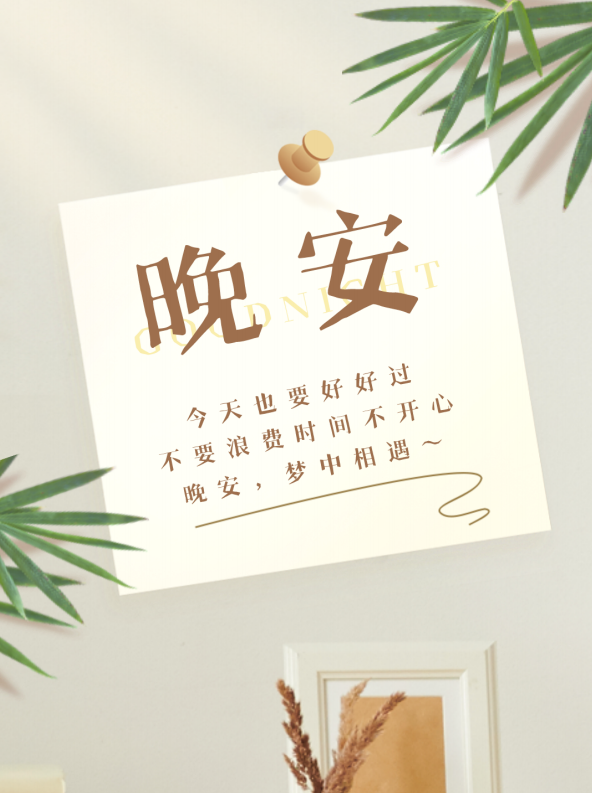
高手庆科手绘宋
Master-ZqkshouhuisongGB
该字体是一款手写感为基础的宋体,字体设计生动灵活。笔画设计保持传统宋横细竖粗的特点,曲线硬朗。横笔画末端加入三角形装饰角,长撇笔画加入转折,与传统宋体撇笔画形成强烈对比,钩笔画笔形细长,略微上挑,具备更强的趣味性的视觉效果。
沿袭中文的设计特点,西文符号以直硬转折的直线为主,加西文风格和中文搭配风格更为统一。